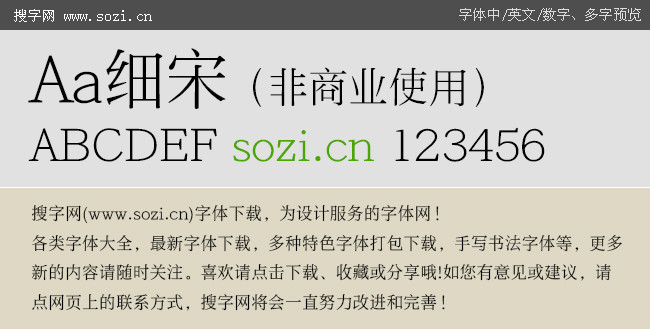
Aa細(xì)宋(非商業(yè)使用)
搜字網(wǎng)給大家提供一款A(yù)a細(xì)宋(非商業(yè)使用)中文字體下載,該字體字形端正,簡(jiǎn)潔大方,整體效果出色,適合海報(bào)設(shè)計(jì)、包裝畫(huà)冊(cè)等宣傳廣告等應(yīng)用(此字體為個(gè)人非商用版,商用可以聯(lián)系QQ:1006760504)。